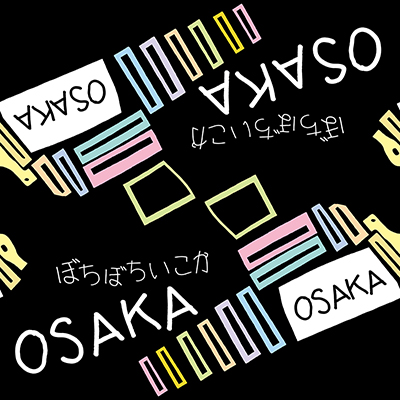
ぼちぼちツインズ
無理せず、気負わず、ボチボチ行きましょう
初めて兄弟コラボの作品を作って下さりとてもうれしいです。ぼちぼち頑張ってくれてこれからもぼちぼちやっていってくれればいいなぁと思います。(母 福子さん)(信谷弘光・信谷優功)
なにわふぉんとのスローガン「ぼちぼちいこか」を信谷さんご兄弟の作品で表現しました。お二人の作品にはそれぞれ違う個性があり、家族も多様性でできていることを実感しながら組み合わせました。(澤田明子)
弘光さんと優功さんは双子で、二人とも自閉症です。弘光さんは細いペンを使い、細かく塗った作品を制作しています。優功さんの作品の特徴は、好きなドラマやアニメのタイトルと一緒に好きな食べ物や風景、物を描きます。なにわふぉんとを機に、双子である二人の作品が重なった時に二人でひとつの新しい世界が誕生しました。(アトリエライプハウス)